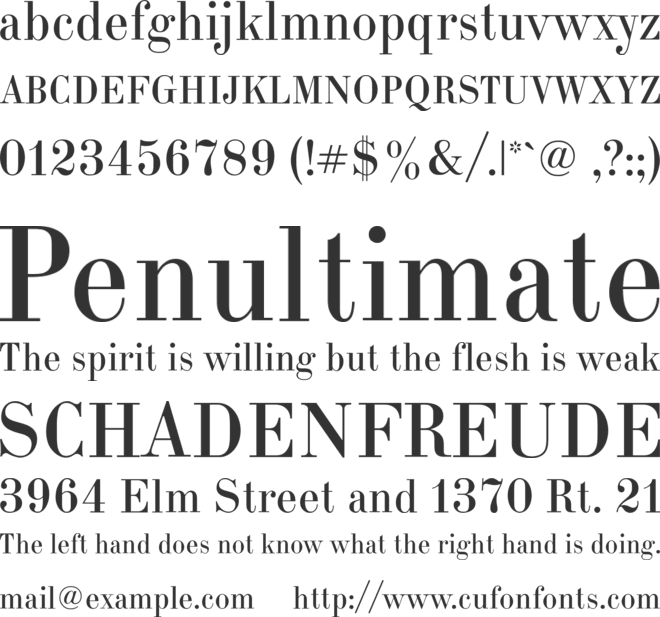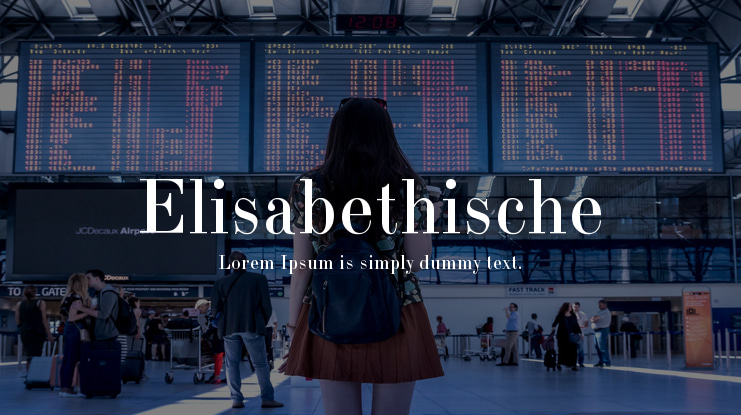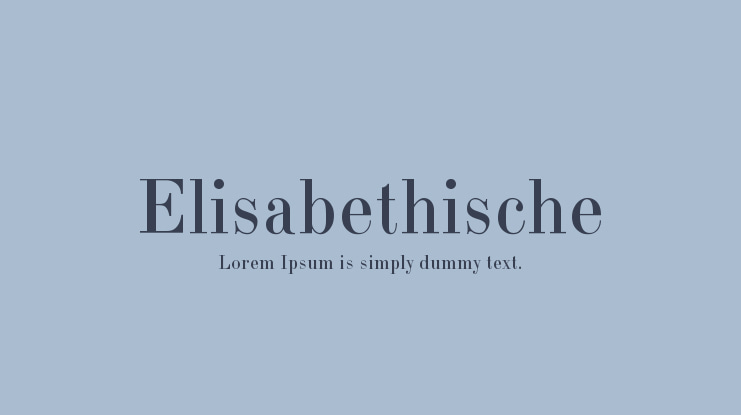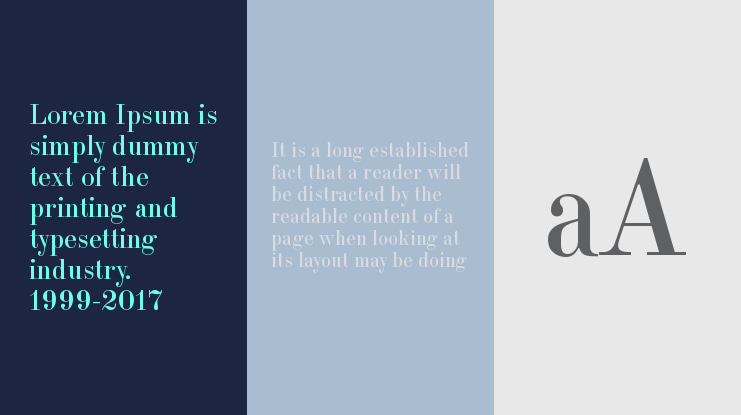
Die mein Version der berühmten «Jelisawethinskaja» Lehmann-Garnitur 1904, mit Ergänzungen deutscher Umlaute und des «sz» («ß»), die für ine vollwertige Förderung der deutschen Sprache notwendig sind, sowie samt eines Paars Buchstaben mit dem Makron, die für die Wiedergabe von Gräzismen mittels lateinischer Schrift notwendig sind, sowie des neu eingeführten russischen Rubelzeichens «₽».